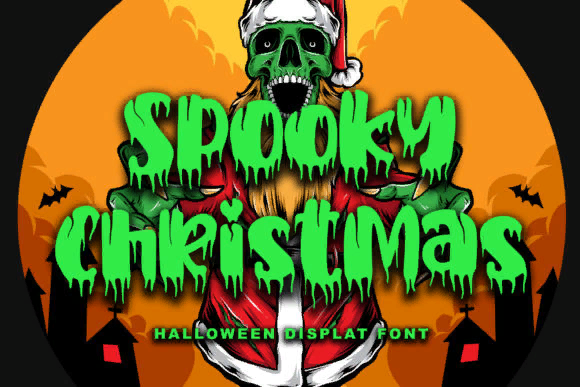
Название: Spooky Christmas Font (2021)
Spooky Christmas - это толстобуквенный и жутковатый шрифт.
Он прекрасно подходит для любого проекта или идеи, связанной с Хэллоуином!
Название: Spooky Christmas Font (2021)
Spooky Christmas - это толстобуквенный и жутковатый шрифт.
Он прекрасно подходит для любого проекта или идеи, связанной с Хэллоуином!